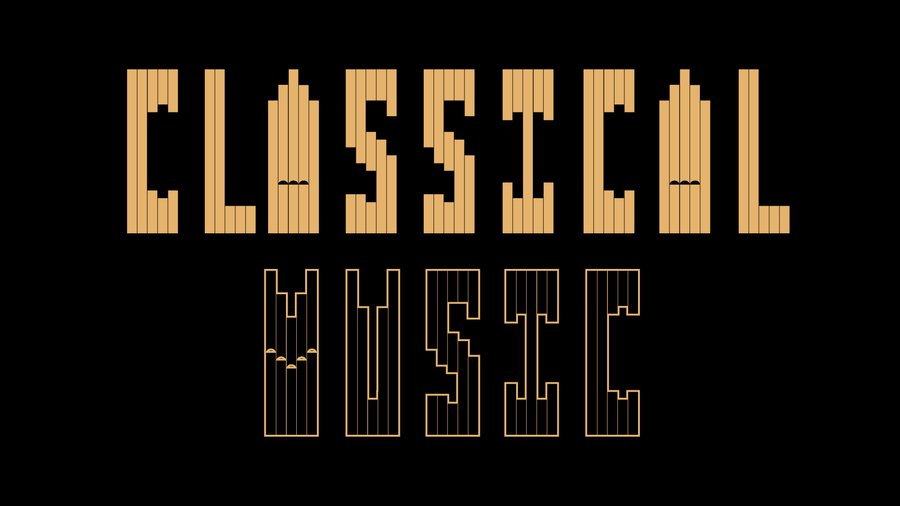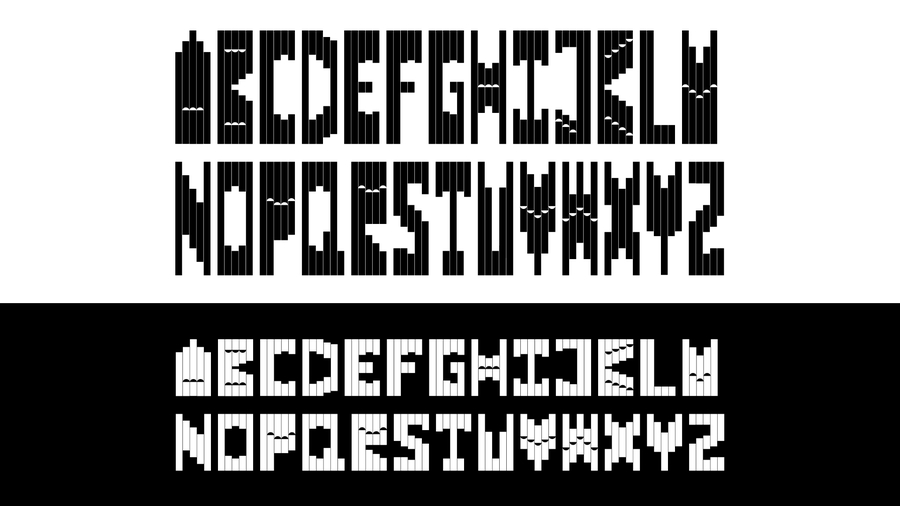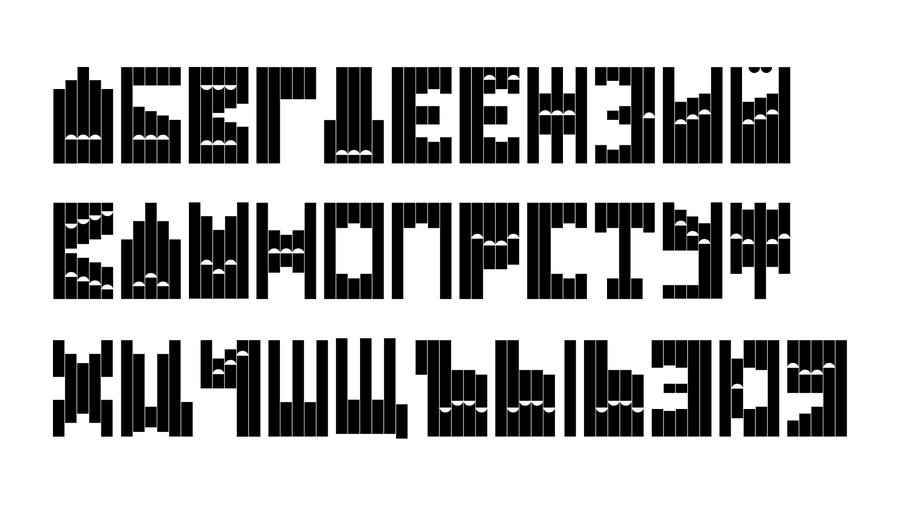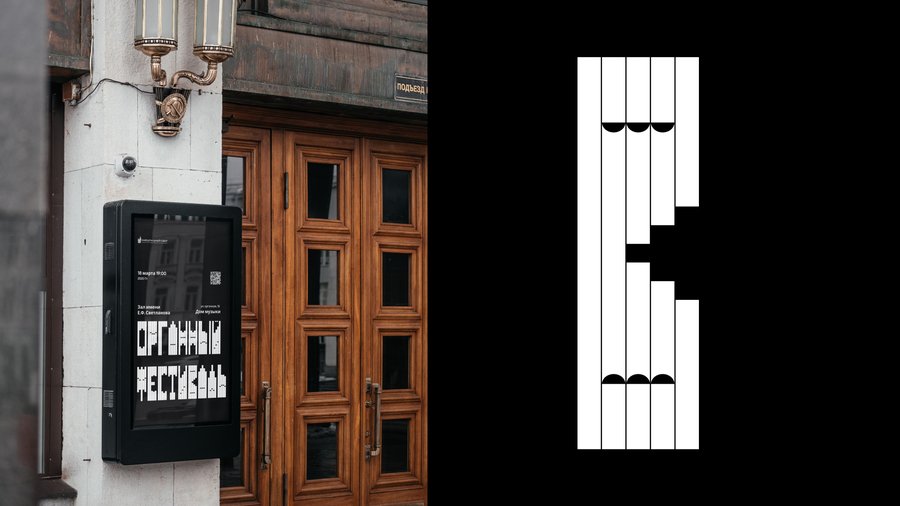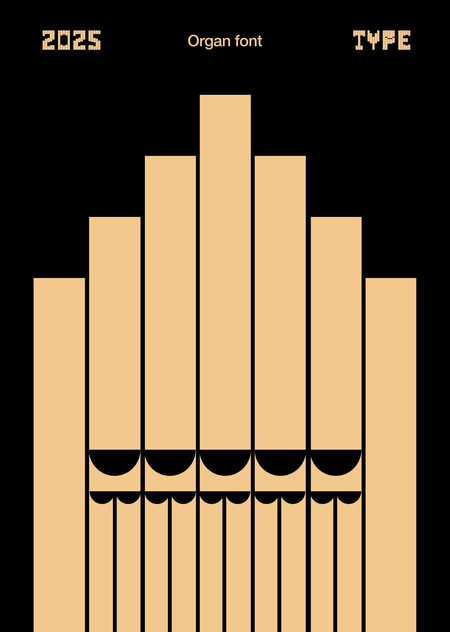
Organ Font — шрифт, вдохновлённый архитектурой и звучании органной музыки. Его вытянутые буквы работают как музыкальные регистры, создавая ритм и вертикальную структуру. Типографика передаёт монументальность, акустику и строгость органного звучания.